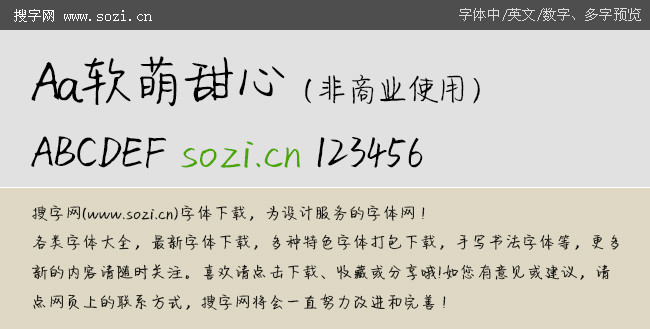
Aa軟萌甜心(非商業(yè)使用)
搜字網(wǎng)給大家提供一款A(yù)a軟萌甜心(非商業(yè)使用)中文字體下載,該字體是一款手寫中文字體,這款字體可愛,充滿童真,適合包裝設(shè)計、書裝設(shè)計、海報設(shè)計等應(yīng)用(此字體為個人非商用版,商用可以聯(lián)系QQ:1006760504)。